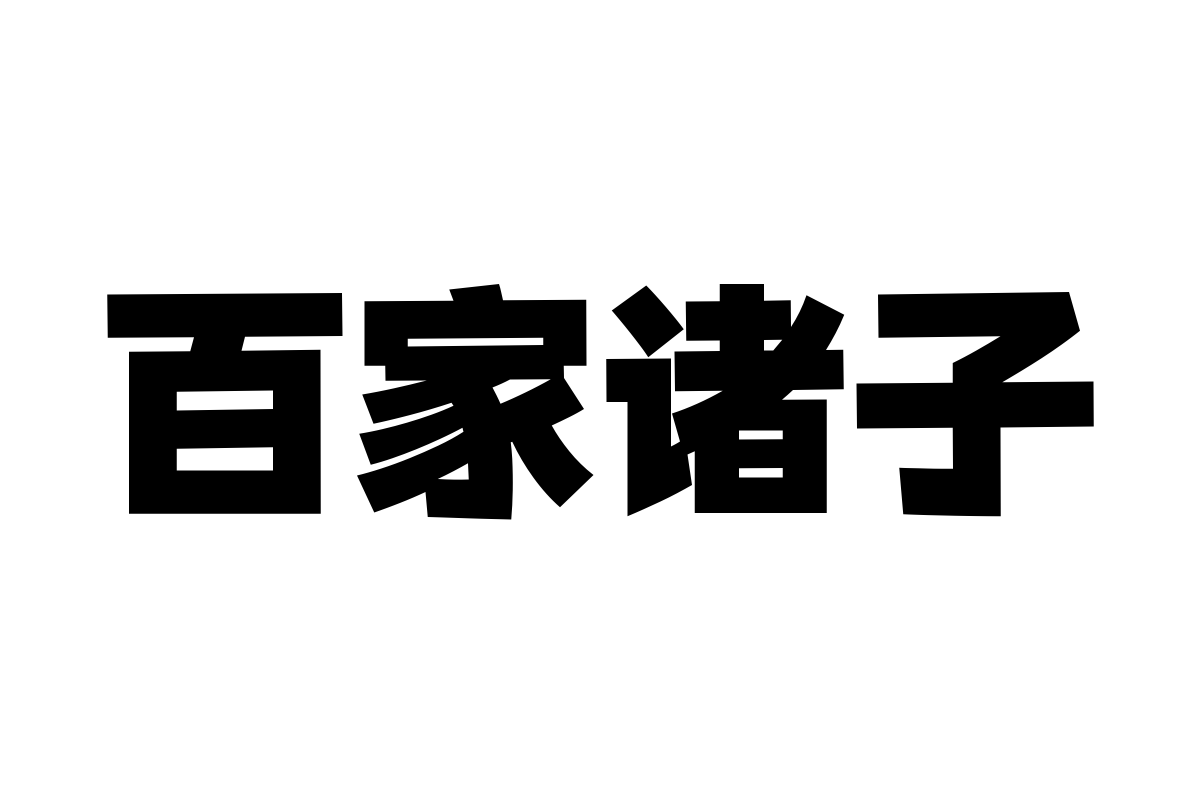
汉仪元隆黑-105 是一款具有现代感和科技感的字体,适用于各种商业、办公、设计等领域。其特点是笔画流畅、字形简洁、易于阅读,同时具有较强的视觉冲击力和辨识度。这款字体的特点是线条粗细适中,笔画饱满有力,给人一种强烈的视觉冲击感。
此外,汉仪元隆黑-105 还具有很好的可读性,无论是在印刷品还是电子屏幕上,都能清晰地展现文字内容。它的设计灵感来源于现代科技元素,使得整个字体充满了未来感和科技感,非常适合用于需要强调科技感和现代感的设计作品。
总的来说,汉仪元隆黑-105 是一款非常优秀的字体,无论是在视觉冲击力还是可读性方面都表现出色,是设计师们不可多得的好选择。